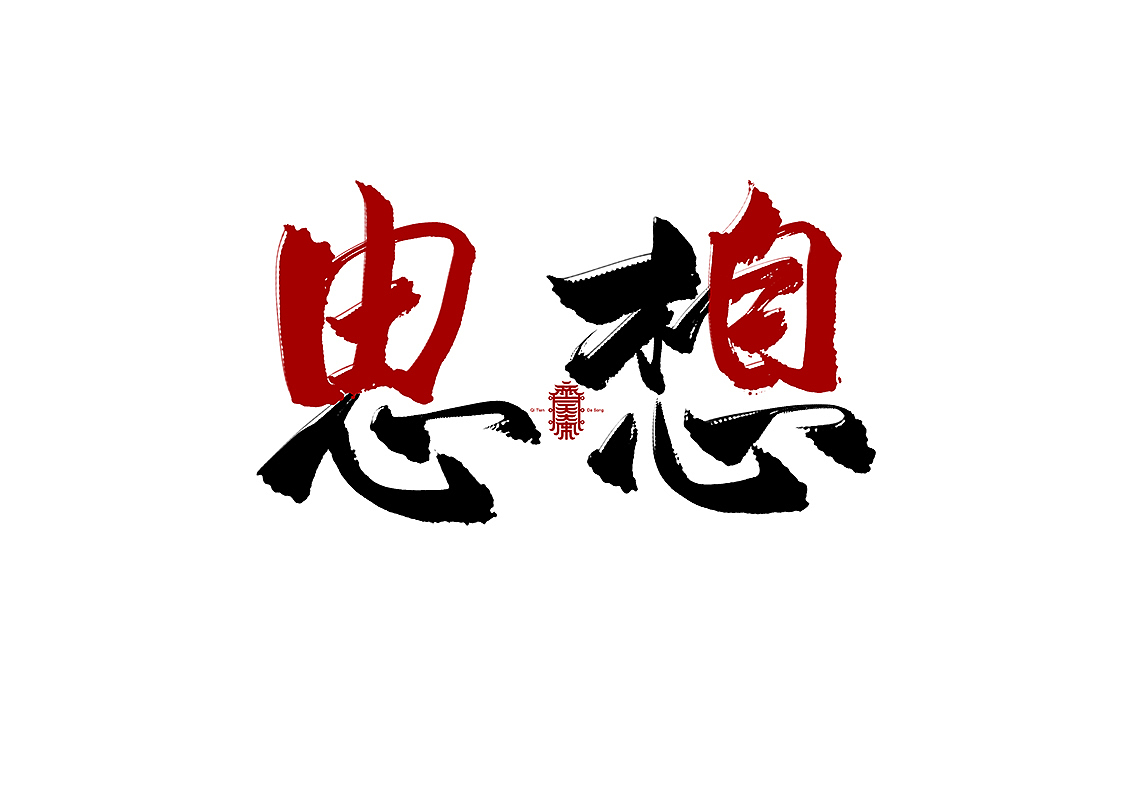
年底了,事儿挨事儿,尽力坚持着“写写画画”系列,之前发了一次,得到了很多朋友的鼓励,还有朋友问我是不是不画画了哈哈哈,没有没有(捂脸)
其实就是前一段尝试了一次之后无法自拔,觉得文字加画画真的是能迅速表达很多内容,是很好的记录思路的好办法,其实就是用这种形式在整理和积累思路,于是用这种方式记录自己的生活(和大家的生活哈哈,这次的“好扎心”送给部分老铁哈哈哈哈)
之前有很多朋友问我是咋想出来的,没别的办法啊,脑子多转转,小手多动动呗
一天“画字”,突然发现的,中国字真是好玩
是好是坏,自己心里要有杆秤
别依赖,多动动脑子
车水马龙的套路多
回不去的名字